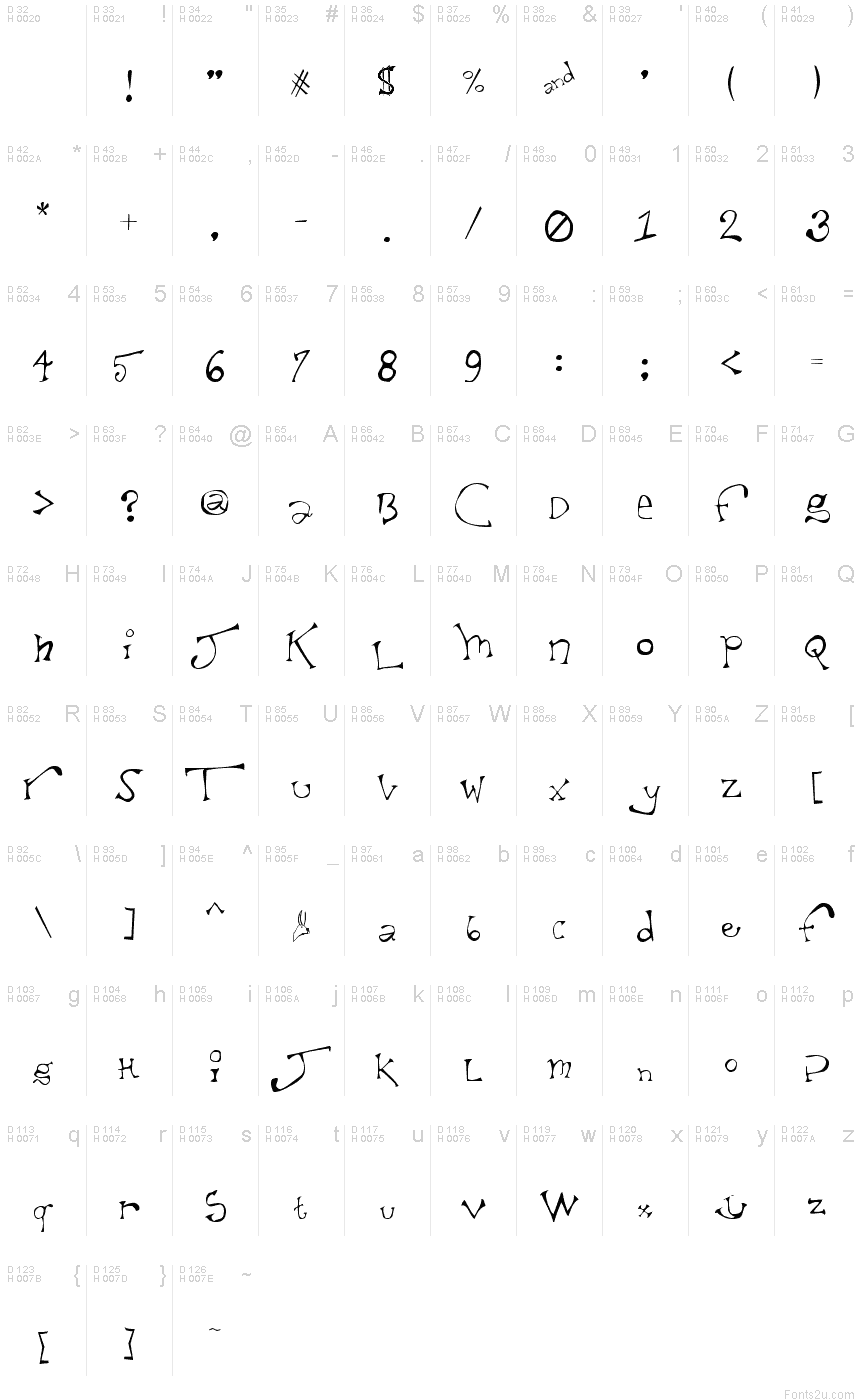
Taxidermist II von Matthew Austin Petty ist eine kostenlose Handschrift mit der seltsamen Atmosphäre eines viktorianischen Jahrmarkts. Die Buchstaben kombinieren lange, auslaufende Striche mit kugeligen, tintenlastigen Formen – eine Mischung aus Skizzenbuch-Schrift und einem Schild aus einem Kuriositätenkabinett.
Damit eignet sie sich perfekt für Plakat-Titel, Albumcover, Zine-Überschriften, Buchumschläge und unheimliche Verpackungen, wo ein Hauch von Unbehagen gefragt ist. Als kostenlose Schrift glänzt sie vor allem in kurzen Displays, Monogrammen und Titelkarten, denn ihre übertriebenen Kontraste und exzentrischen Kurven kommen bei wenigen Wörtern besser zur Geltung als im Fließtext.